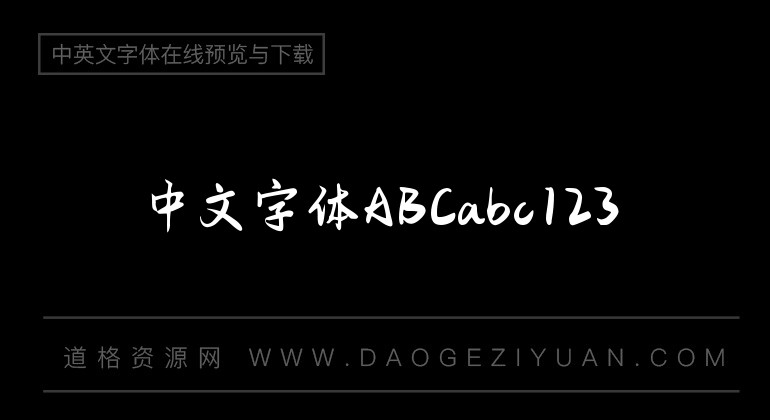
Aa竹下听潇梦
Aa竹下听潇梦是一款由「AaFont」发布的日文自由书体字体。它是一款极具特色的字体,以轻松自然的书写形式表现出清新优雅的气质。Aa竹下听潇梦字体采用简洁的线条设计,拥有清新柔和的字形,适合用于日常文字书写,也可以用于设计创作,以及印刷等多种用途。
Aa竹下听潇梦是一款非常不错的手写艺术字体,具有很好的视觉感,适合于文化类的宣传设计、商业类品牌的广告和产品包装设计以及个性化文字排版等较多场景。
Aa竹下听潇梦字符映射图